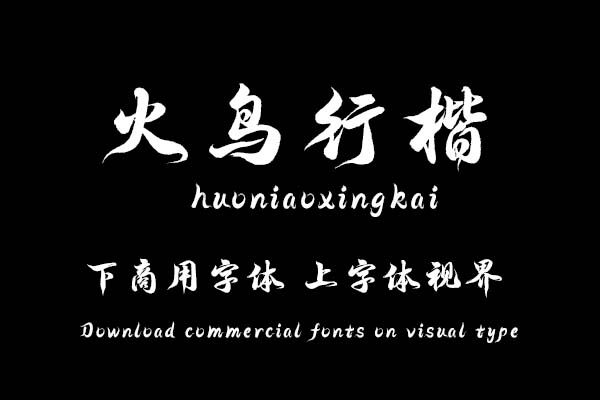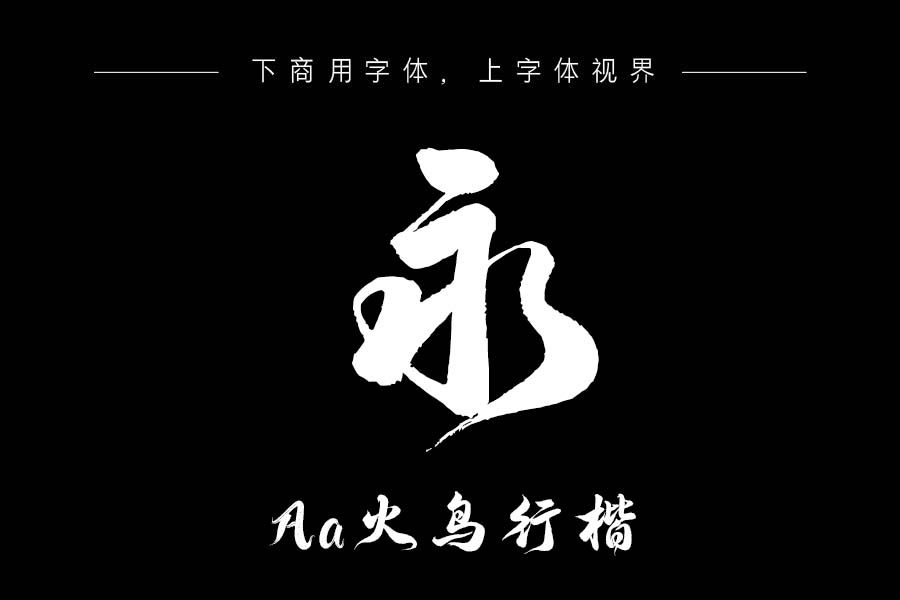
本字体书写灵活顺畅,融合行书风格,书写时主要笔画拖出波纹线条,增强字体的不安感,钩呈蜡烛形状结合毛笔书写笔触,增强字体的诡异氛围。购买须知:“下载服务费”与“字体VIP”所获得字体 仅用于个人非商用, 商用请联系付费授权。本字体为电脑用字,手机没有root权限不支持直接手机换字(手机如何root,请自行百度搜索教程)。购买前请先 了解清楚后再付款 ,字体为虚拟产品无法回收 一旦购买不支持退款。